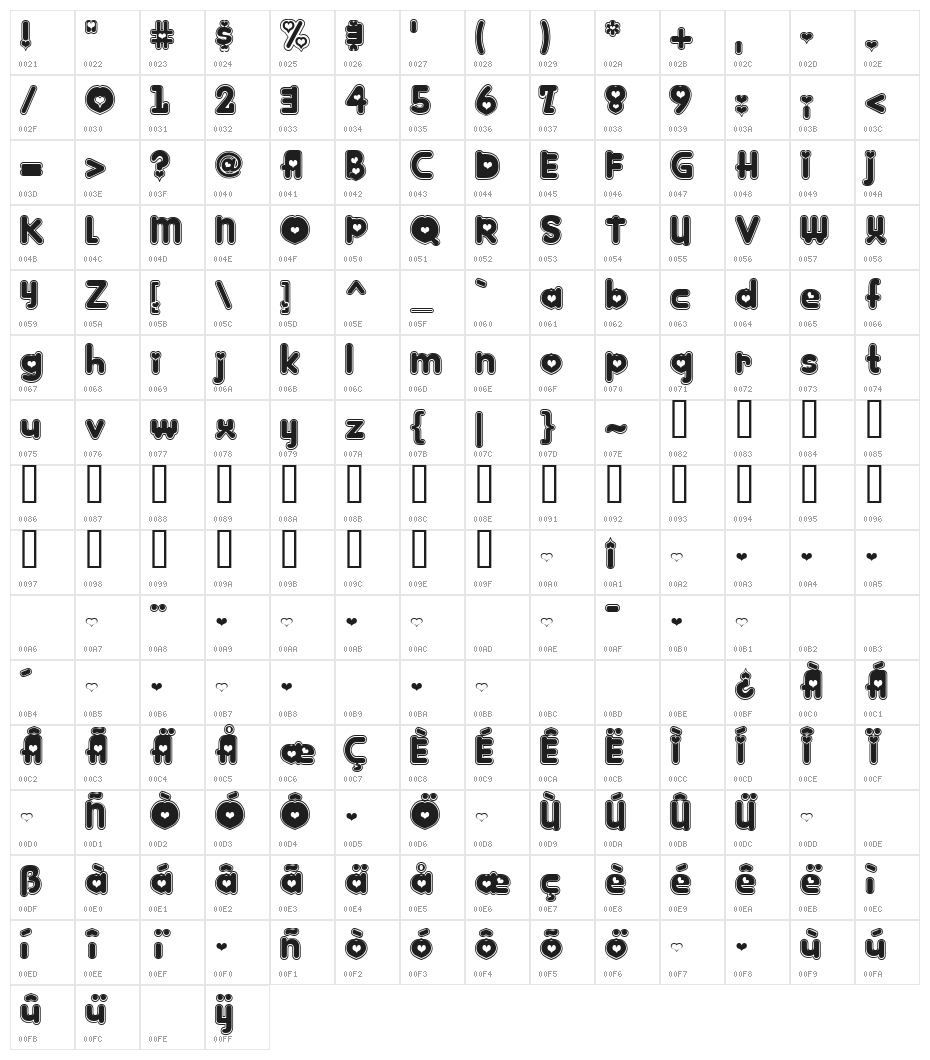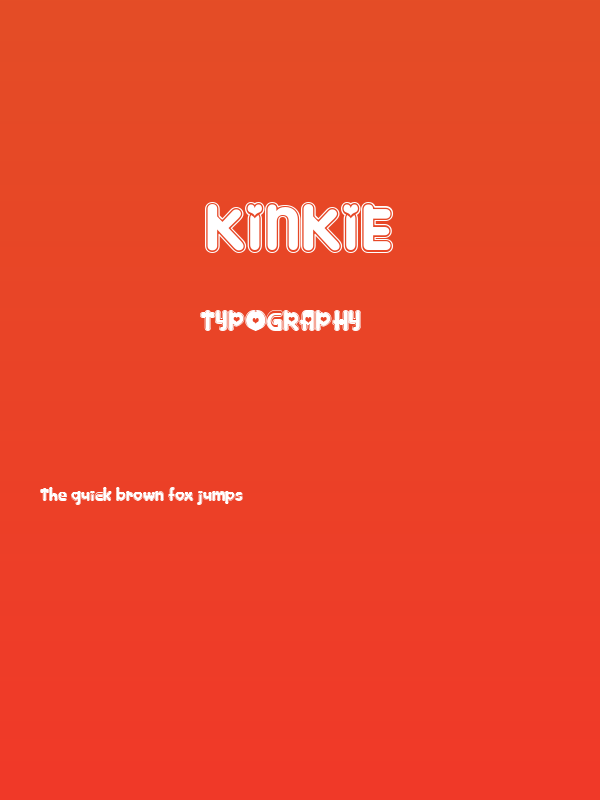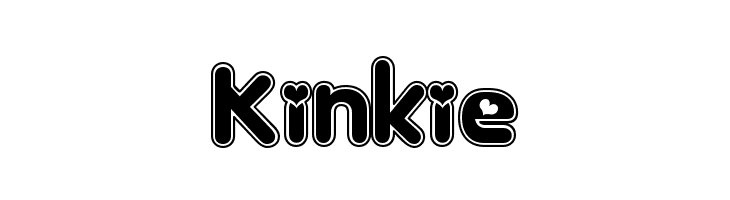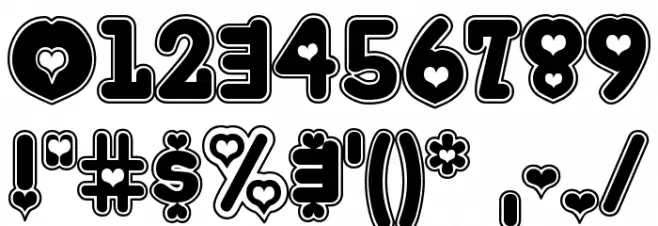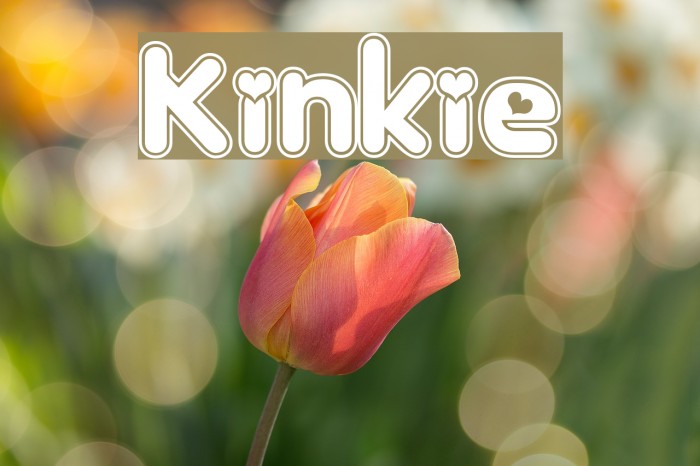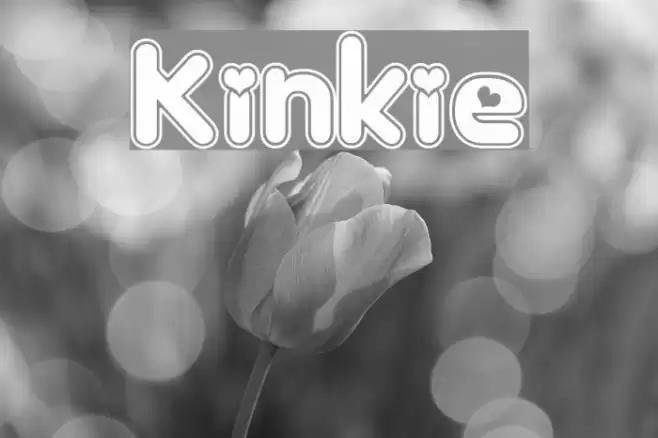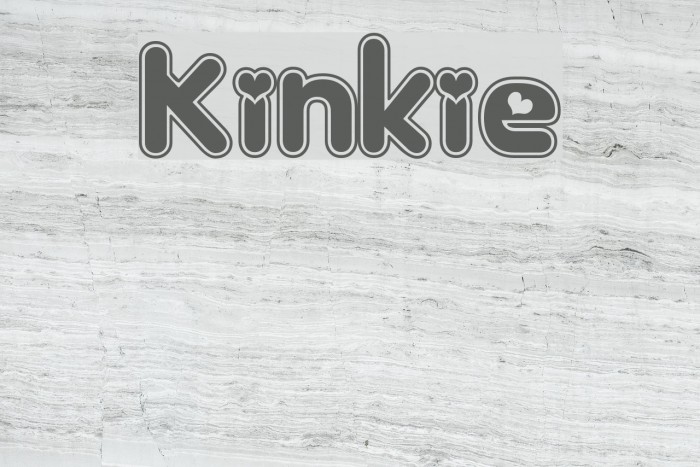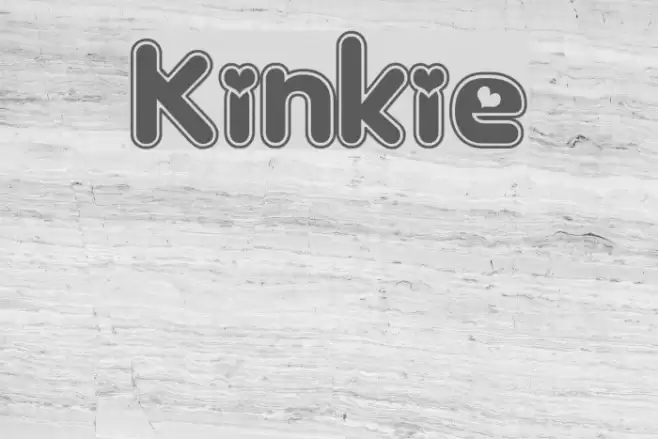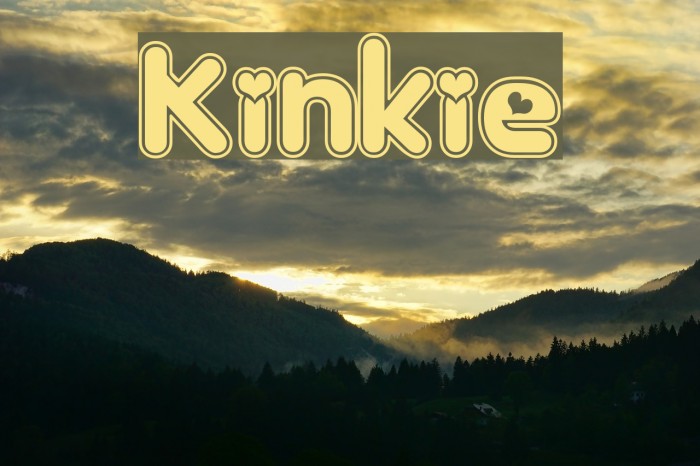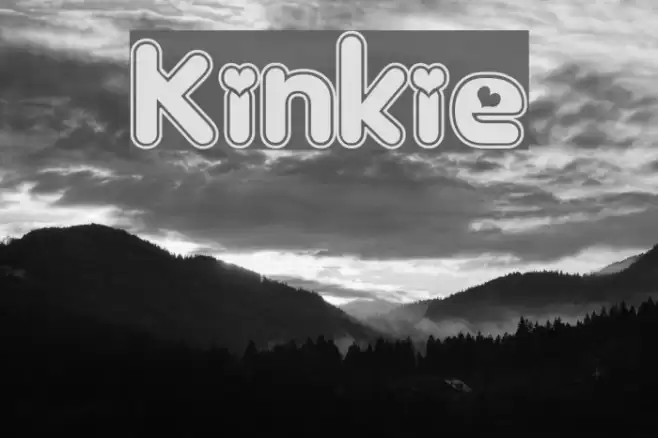
Kinkie Font
✎ Decorative
| Categorías | Decorative |
| Estilo general | Playful, Romantic |
| Caso de uso | Headlines, Logos, Invitations |
| Proyectos propuestos | Ideal for Valentine's Day cards, children's party invitations, playful branding, and romantic-themed posters. |